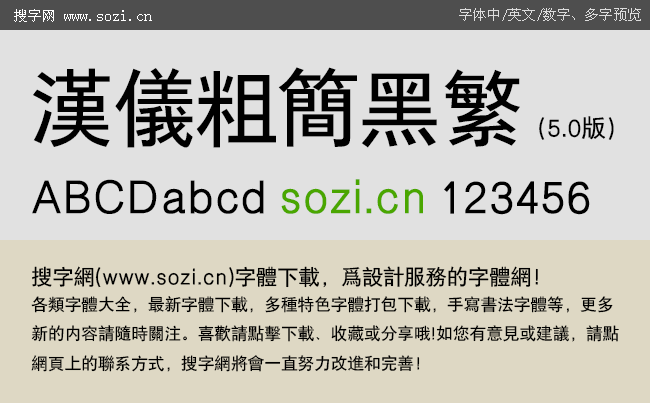
漢儀粗簡(jiǎn)黑繁5.0
搜字網(wǎng)提供一款漢儀粗簡(jiǎn)黑繁中文字體下載,漢儀粗黑保持著黑體字的共有特點(diǎn),筆畫(huà)粗壯有力,橫豎筆畫(huà)粗細(xì)比較接近,兩端平直,加鋒較小,筆畫(huà)簡(jiǎn)潔粗壯,厚實(shí)有力。可用于報(bào)刊雜志排版,也適用于平面廣告,圖書(shū)印刷等廣告設(shè)計(jì)場(chǎng)合使用。